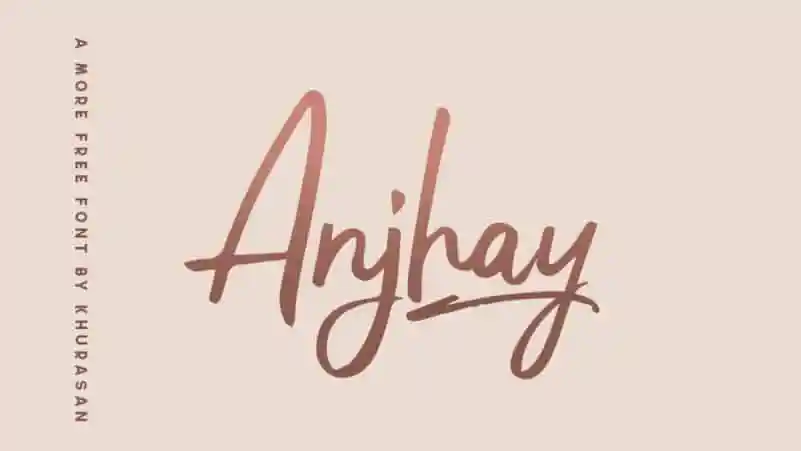
Anjhay Script Font – Download Grátis
Anjhay Script Font é uma fonte elegante que surge com uma beleza única e autêntica, inspirada na arte do traçado manual. Esta fonte contém todo um conjunto de letras maiúsculas e minúsculas, uma ampla variedade de pontuação, números e suporta várias línguas. O Anjhay Script é uma fonte livre que traz ao usuário um aspecto natural e realista. Sujeito a várias aplicações como redes sociais, cartões, trabalhos artesanais e citações, ele proporciona o aspecto desejado para qualquer projeto visual. Uma fonte perfeita para quem busca estilizar suas criações de forma simples mas com uma beleza impressionante.